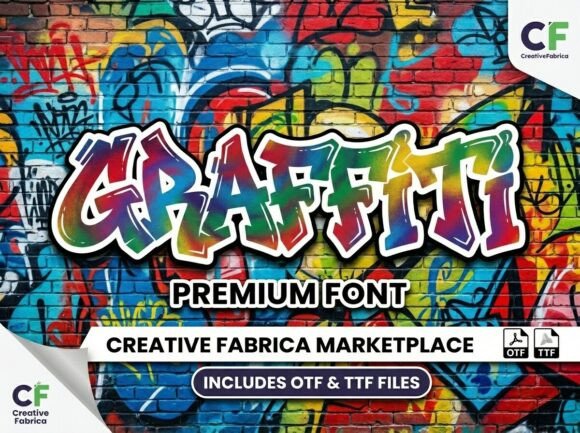
Graffiti
Si vous recherchez des ressources de haute qualité comme Graffiti, ce pack premium est un choix fantastique pour vos projets créatifs.
Conçu avec précision, Graffiti offre des vecteurs nets, une typographie fluide et une licence commerciale pour une tranquillité d'esprit.